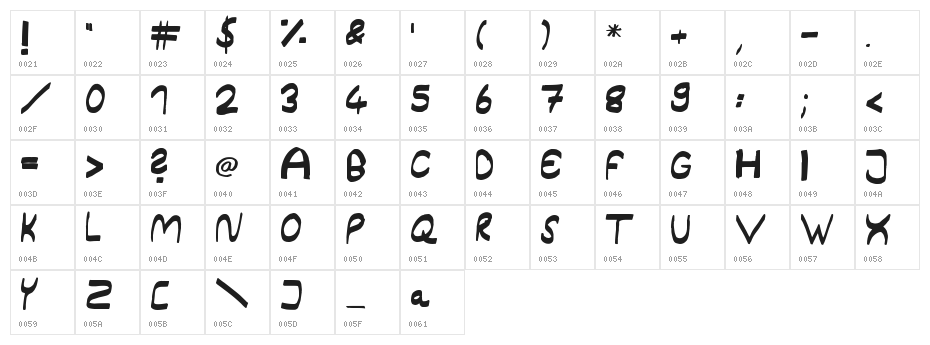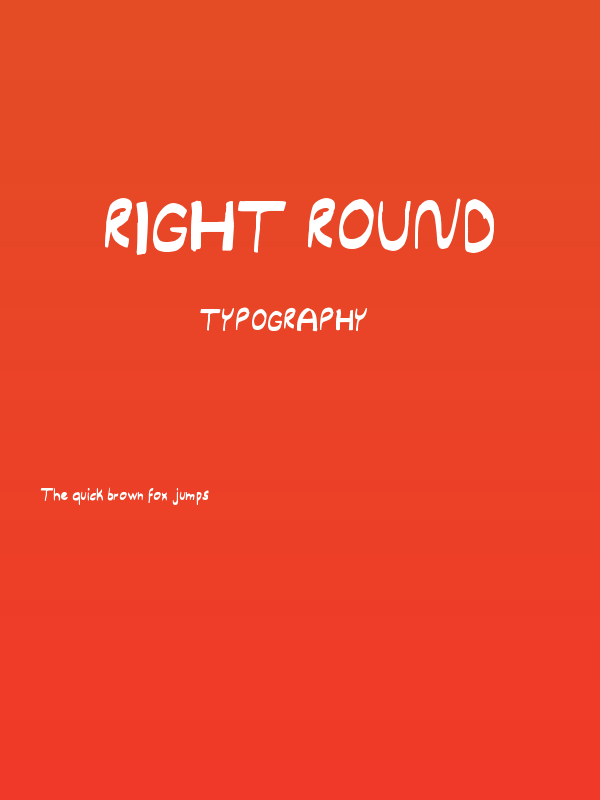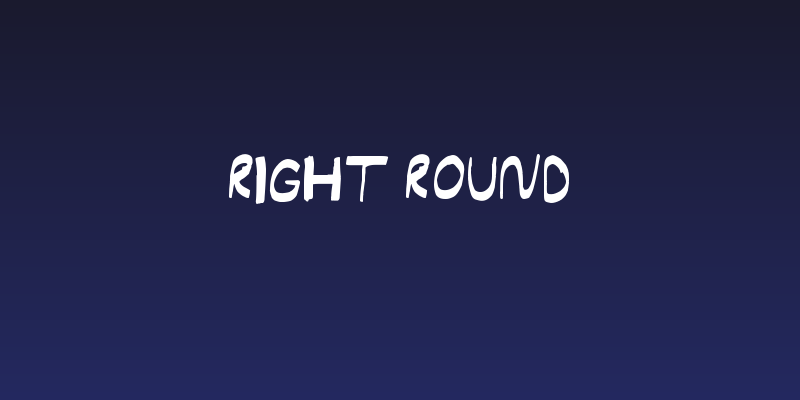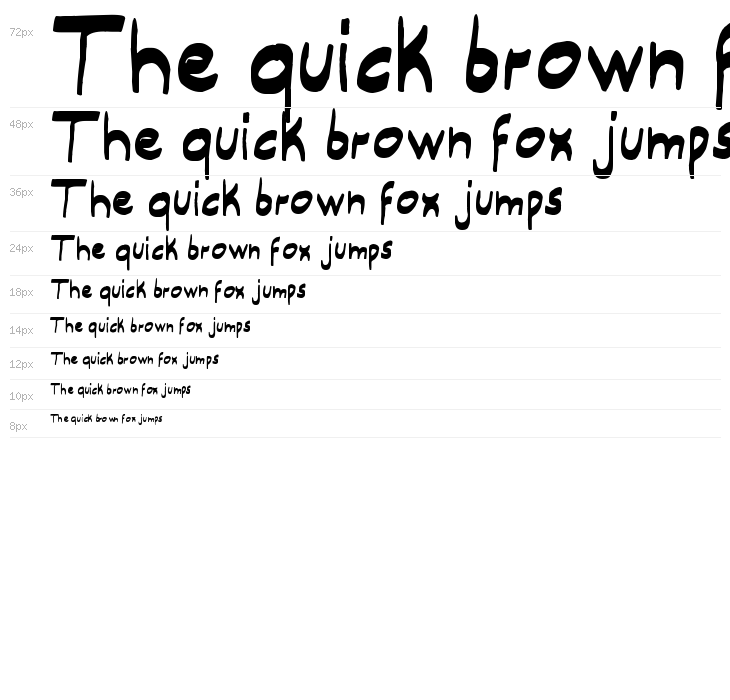
Right Round Font
| Gesamtstil | Playful, Casual |
| Anwendungsfall | Headlines, Logos, Informal Text |
| Vorgeschlagene Projekte | Ideal for children's books, casual invitations, playful branding, and social media graphics. |